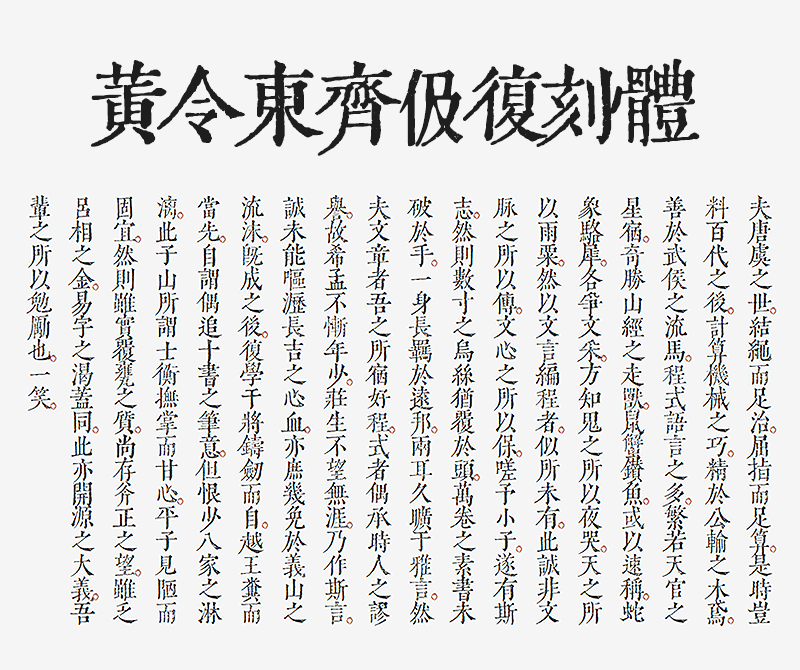
黄令东古风字体有两款,分别为「黄令东齐伋复刻体」和「黄令东齐伋体」
黄令东齐伋复刻体
采用半自动计算机视觉和OCR对《李長吉歌詩》和《淮南鴻烈解》进行扫描,通过程序处理后再手动选择适合的字型,最后导出成字体文件。因为是古籍进行处理而得到的字体,所以只有繁体字形。在使用字体的过程中,如果输入简体字会直接映射成繁体字形。
黄令东齐伋复刻体
黄令东齐伋体
一款可以媲美康熙字典体的免费商用字体,黄令东齐伋体是基本思源宋体改造而来,所以对中文汉字支持极佳,字库完整无论是简体还是繁体都基本上不缺字。
黄令东齐伋体
字体作者
LingDong Huang 已经 GitHub 上放出制作这款字体的工作流,大家有兴趣可以查看字体的效果。